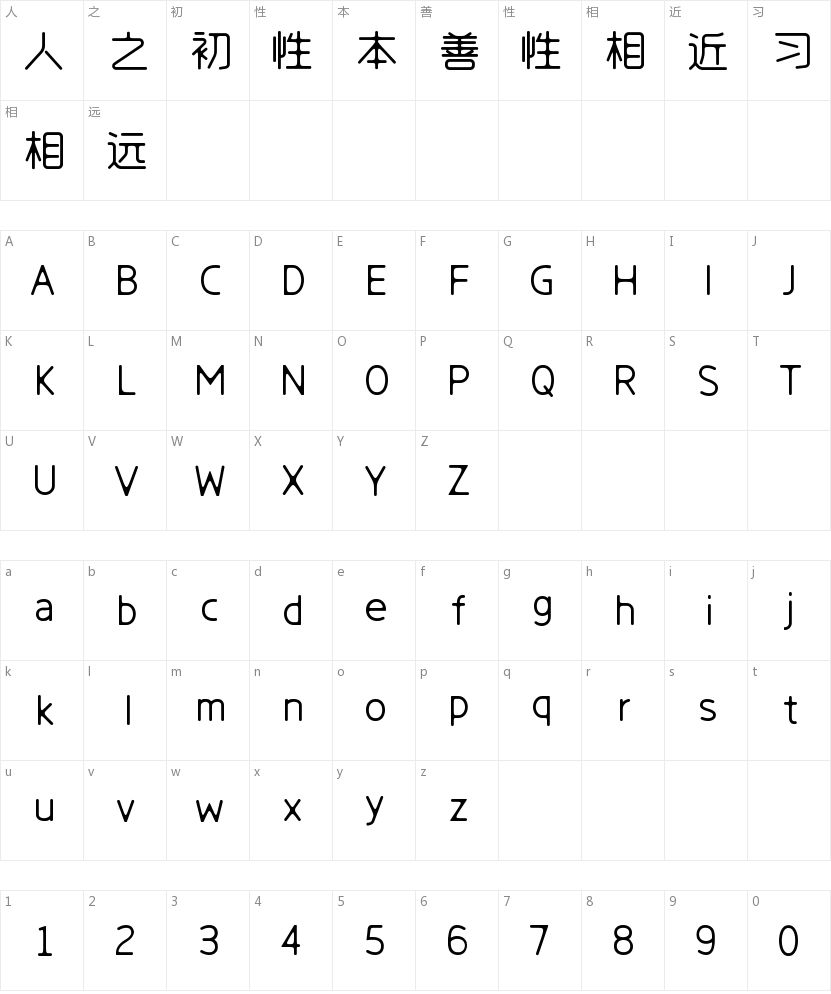
字心坊韵圆体
字心坊韵圆体是一款经典的中文字体,它由中国著名的字体设计师“字心坊”设计,是一款非常传统的中文字体,让人耳目一新。字心坊韵圆体采用现代技术,将传统的中文字体设计和现代技术结合,让中文字体更加时尚和精致。字心坊韵圆体具有清晰的线条,优美的曲线,柔和的笔画,让字体更加精致,更具有艺术性。字心坊韵圆体可以用于印刷、网页设计、排版等,是一款非常适合中文字体的经典之作。
字心坊韵圆体是一款非常不错的手写艺术字体,具有很好的视觉感,适合于文化类的宣传设计、商业类品牌的广告和产品包装设计以及个性化文字排版等较多场景。